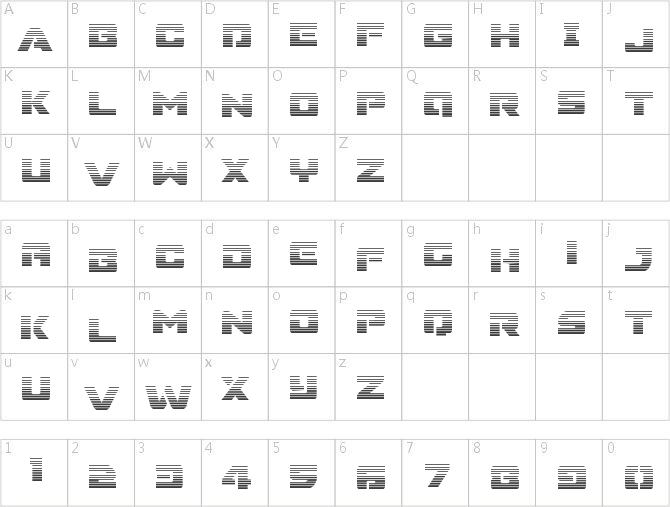
Super Commando Gradient 詳情頁
Super Commando Gradient字體字庫是一款讓人賞心悅目、百看不厭的英文字體,適合各類廣告和產(chǎn)品包裝設(shè)計應(yīng)用,字體大小0.06MB,格式為ttf字體,上傳用戶是志誠設(shè)計,作者/版權(quán)方為未知